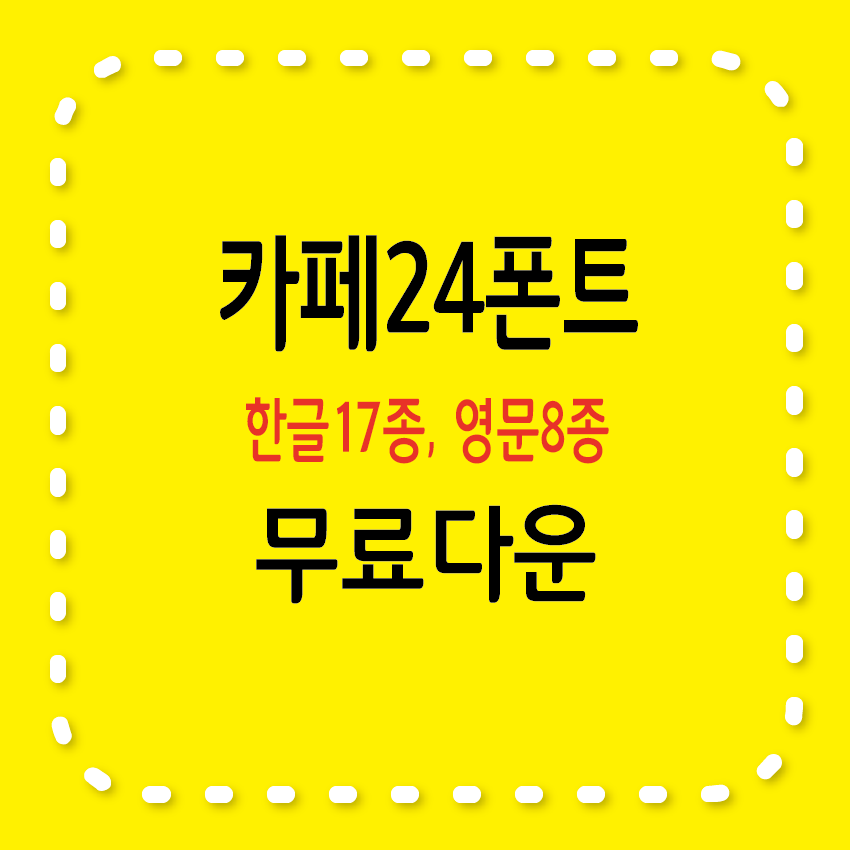
카페24 한글폰트
카페24 한글폰트로는 모야모야, 슈퍼매직, 클래식타입, 써라운드, 아네모네 에어, 아네모네, 빛나는별, 고운밤, 당당해, 단정해, 심플해, 동동, 쑥쑥, 숑숑이 있습니다. 제목용 서체, 손글씨, 흘림체 등 다양한 서체가 있습니다.
카페24 영문폰트
카페24 영문폰트로는 Cafe24 Behappy, Cafe24 Decobox, Cafe24 Decoline, Cafe24 Decomilk, Cafe24 Decoschool, Cafe24 Decoshadow, Cafe24 Decozoo, Cafe24 Loving U 이렇게 8종류가 있습니다.